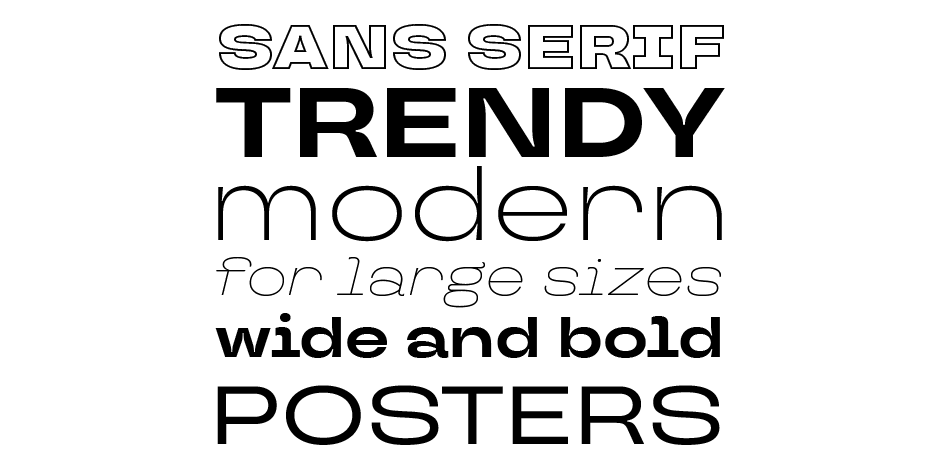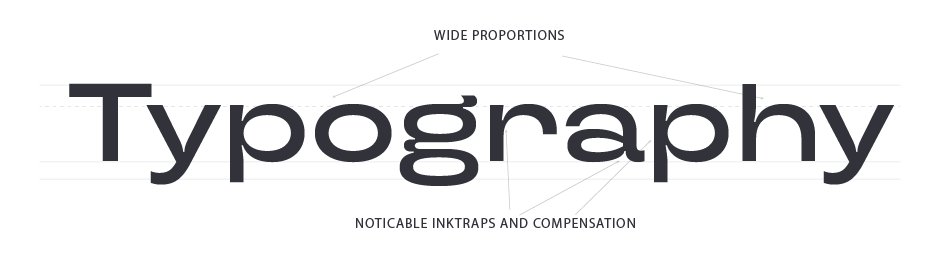
TT Travels Next es una moderna sin gracias ancha diseñada para llamar la atención. Tras su lanzamiento, se ha hecho un hueco en el mundo de las carteleras y los carteles de espectáculos, así como en los envases.
El tipo de letra TT Travels Next consta de 21 fuentes: 9 estilos verticales y 9 inclinados, dos estilos de contorno y un fuente variable con dos ejes de variabilidad (anchura e inclinación).
- En las caras oblicuas, el ángulo de inclinación se ha aumentado intencionadamente hasta 14 grados, para que pueda escribir inscripciones dinámicas nítidas.
- Hay dos caras de contorno en la familia fuente , que encajan perfectamente con las verticales y las complementan.
- Además, las proporciones de la familia son muy amplias y los personajes casi no se estrechan al pasar de una cara gruesa a una delgada.
TT Travels Next es una nueva versión de TT Travels fuente, más moderna y atrevida.
TT Travels Next es un experimento que responde a la pregunta: "¿Y si el TT Travels original tuviera un aspecto diferente, menos comprometido y más radical?".
TT Travels Next se diseñó para su uso en grandes tamaños y encabezados, pero posee un conjunto estilístico tranquilo con formas de caracteres más tradicionales, lo que le permite ser legible en textos.